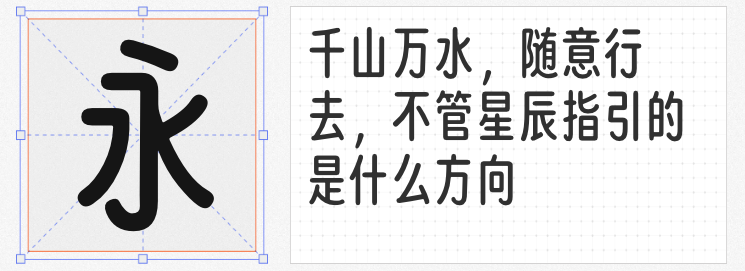
立冬作为冬季的序章,承载着万物收藏、蓄势待发的文化意象。在节气主题设计中,字体不仅是信息载体,更是氛围营造的关键元素。以下四款免费商用字体,以不同风格诠释立冬的静谧与生机,为设计注入东方美学基因。
1. 小狼天穹
这款基于日本「解星计划」衍生的字体,以「宇文天穹」为基底补全繁简体字库,笔画间保留了传统汉字的骨力与韵律。其字形结构端庄中见灵动,横竖撇捺的收放自如,恰似立冬时节草木虽凋却暗藏生机的状态。适用于节气海报标题或文化长卷设计,能以古朴气质传递节气背后的文化厚度。
2. USMCC源简特粗体
由思源宋体反向插值制作的特粗版本,在保留宋体结构特征的同时,通过加粗笔画强化视觉冲击力。其横细竖粗的对比与棱角分明的转折,既延续了传统书法的书写节奏,又以现代设计语言诠释立冬的凛冽与坚韧。适合作为主标题字体,搭配冰雪元素或深色背景,可营造出沉稳大气的节气氛围。
3. 一品启航体
以传统书法为根基的这款字体,笔锋昂扬如松柏迎霜,字形结构疏密有致,既保留毛笔书写的飞白痕迹,又通过数字化处理优化阅读体验。其“锐意进取”的视觉语言与立冬“万物收藏实为新生”的哲理不谋而合,特别适合文化传播类设计,能以动态笔势传递节气中的生命张力。
4. 猫啃忘形圆
基于开源字体得意黑改造的圆润版本,通过消除尖锐棱角赋予文字亲和力。其饱满的字形与流畅的曲线,如同立冬时节围炉夜话的温馨场景,适合儿童读物、生活美学类设计。当需要弱化节气寒冷感、强调人文关怀时,这款字体能以柔和视觉传递温暖情绪。
这四款字体以开放姿态供创作者自由使用,从古朴传承到现代解构,从力量表达到温暖治愈,为立冬主题设计提供了多元表达路径。选择与节气内涵契合的字体,方能让设计作品在传递信息的同时,成为承载文化记忆的视觉符号。